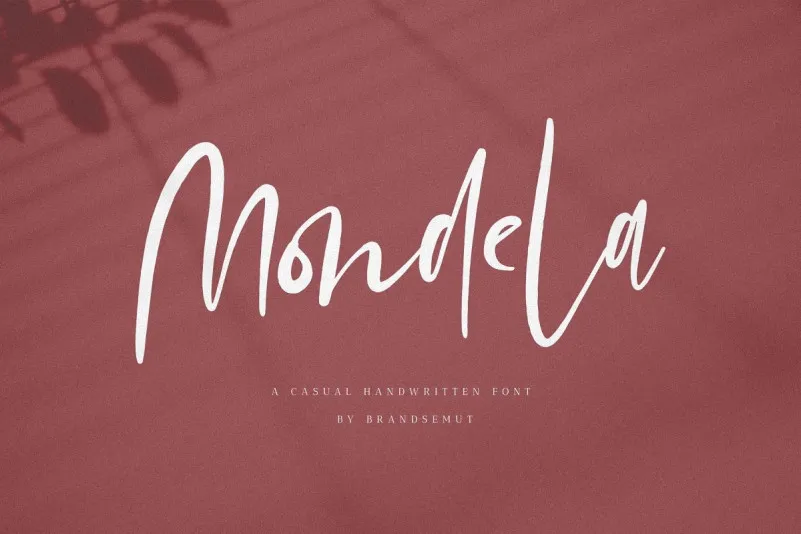
Mondela Handwritten Font – Download Grátis
Estamos muito felizes por compartilhar com você a Mondela Handwritten Font, uma opção única para aqueles que buscam adicionar um toque autêntico e moderno aos seus projetos de design. Esta fonte script vem na forma casualmente escrita, proposta pelo designer M.0Type. Não é apenas uma escolha versátil para qualquer projeto – ela traz um ar elegante e sofisticado ideal para aplicações como logotipos e identidades corporativas, textos de anúncios, citações, cabeçalhos e embalagens. Com 23 ligaturas exclusivas, Mondela Handwritten é uma opção perfeita para aqueles buscando incorporar um aspecto autêntico da escrita manual em seu design. Se você está procurando por uma fonte que se destaca e dá ao seu projeto uma aparência sofisticada e moderna, a Mondela Handwritten é sua escolha perfeita. Com um leque completo de letras maiúsculas e minúsculas, símbolos multilingues, números e pontuações, a Mondela Handwritten oferece flexibilidade suficiente para criar um design verdadeiramente único. Esta fonte foi projetada pela BrandSemut, que nos garante sua qualidade e versatilidade. Compondo com perfeição tanto os detalhes formais quanto os sutis nuances do escrita manual, ela se destaca não apenas como uma opção de texto para aplicativos digitais, mas também para a criação de logotipos, identidades visuais, anúncios e embalagens. Seja para um projeto mais pessoal ou comercial, Mondela Handwritten é uma fonte que merece ser explorada e experimentada em sua totalidade.